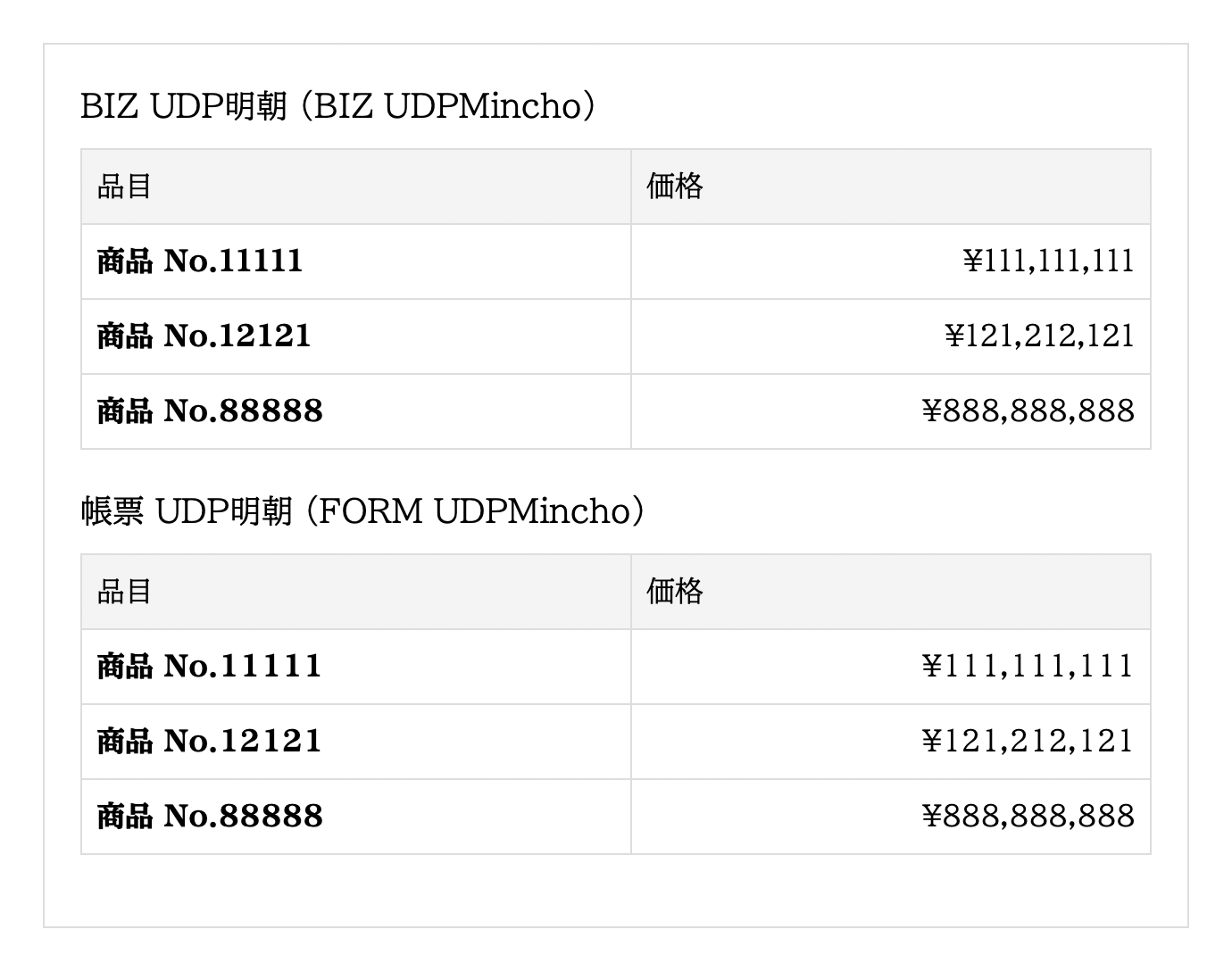
「BIZ UDP明朝」の数字は、0〜9 のうち 1 のみ幅(サイドベアリング)が異なるので、1 のサイドベアリングを変更しています。「BIZ UDP明朝」のグリフ数 13,932個のうち2個を変更し、残りの約 99.9856% のグリフは全く同じです。
「BIZ UDP明朝」は「BIZ UDPゴシック」と異なり、Regular と Bold とで数字の幅が異なるため混在させると等幅にはなりません。つまり、「帳票 UDP明朝」でも Regular と Bold とで幅が異なります。
モリサワ「BIZ UDP明朝」の「1」と「1(全角)」の幅のみを変更し、数字(0〜9)を等幅にしたフォント「帳票 UDP明朝 (FORM UDPMincho)」です。
「帳票 UDPゴシック」を作ったので、明朝も作りました。
「BIZ UDP明朝」の数字は、0〜9 のうち 1 のみ幅(サイドベアリング)が異なるので、1 のサイドベアリングを変更しています。「BIZ UDP明朝」のグリフ数 13,932個のうち2個を変更し、残りの約 99.9856% のグリフは全く同じです。
「BIZ UDP明朝」は「BIZ UDPゴシック」と異なり、Regular と Bold とで数字の幅が異なるため混在させると等幅にはなりません。つまり、「帳票 UDP明朝」でも Regular と Bold とで幅が異なります。